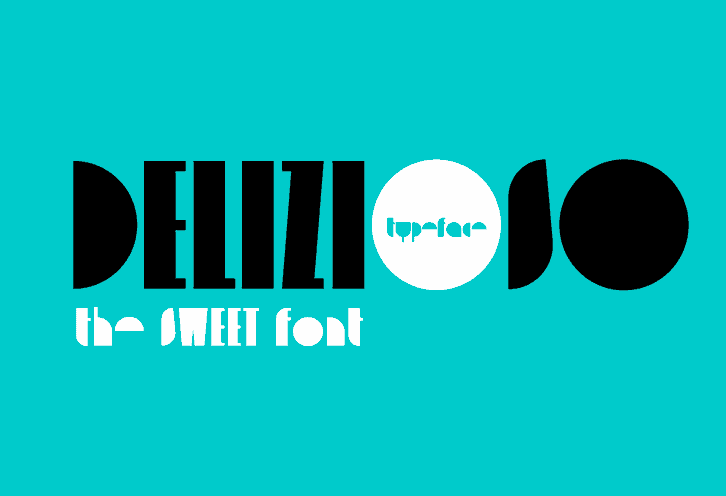
Delizioso Font – Download Grátis
Delizioso é uma nova adição à seleção de fontes display disponíveis para você. Desenvolvida pelo designer Zetafonts, esta fonte geométrica e sans serif lembra as tipografias do período da Segunda Guerra Mundial, revisadas num toque moderno e divertido. Com um impacto gráfico único, Delizioso é perfeito para headlines poderosos e contemporâneos. Esta font se destaca por sua estética clara e elegante, ideal para projetos que buscam destacar-se na tela ou em ambientes digitais dinâmicos. Suas linhas retas e seus traços finos combinam de maneira perfeita com a sensação de revigoramento moderno deste design, tornando Delizioso uma escolha inigualável para quem procura um visual brilhante e único em seu próximo projeto visual.